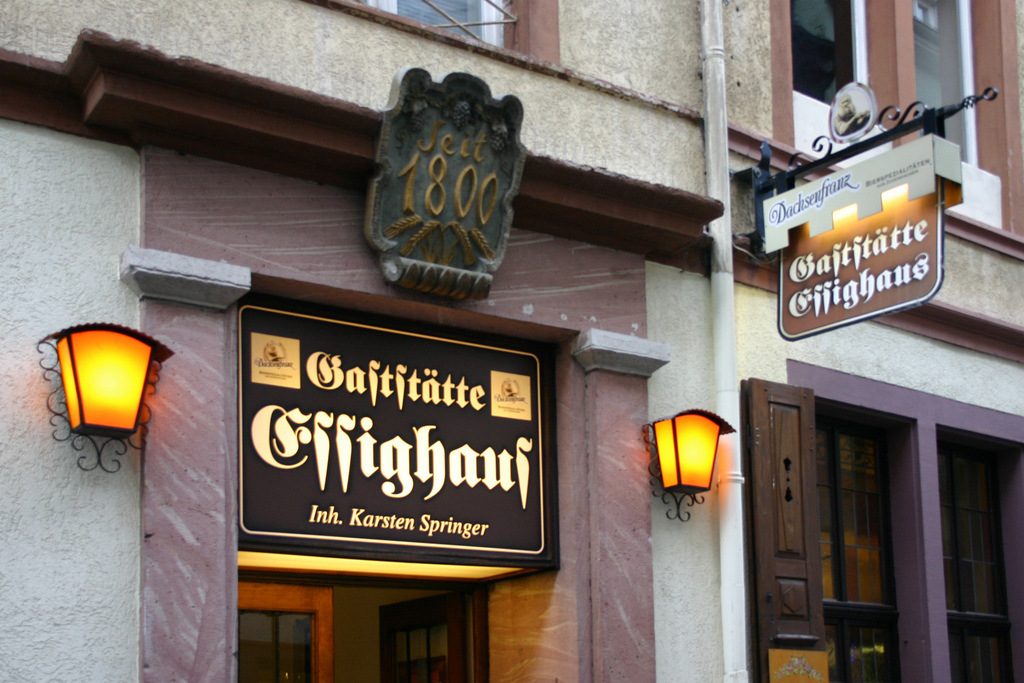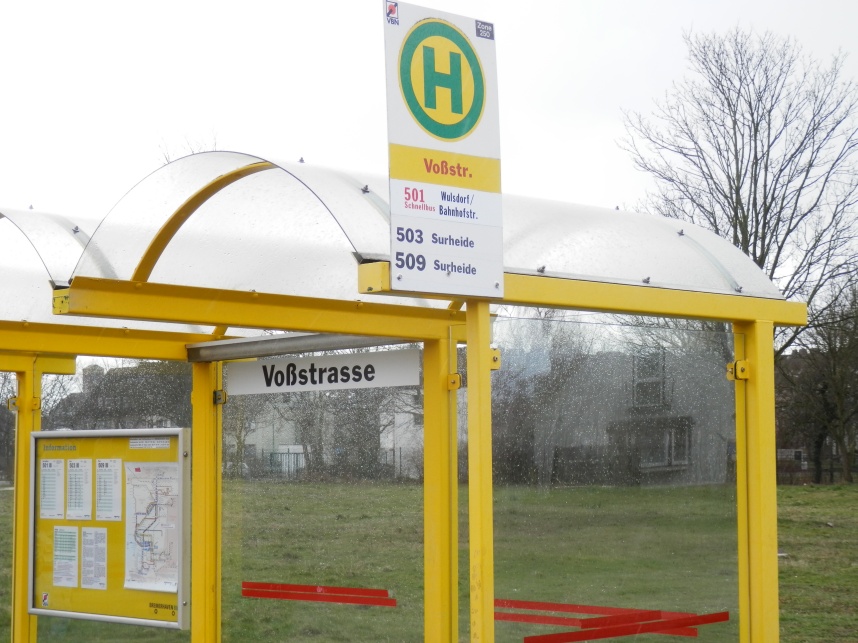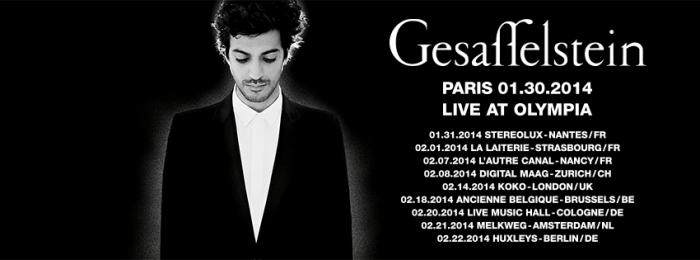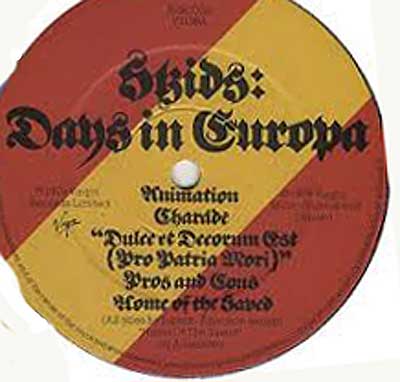
Neue Rechtschreibung?
Mir sieh diese Unsaubere Kantenführung einzig als das Ergebnis eines Autotracings aus.
Das war ja auch mein erster Gedanke, aber wenn man schon einen Billigklon einer bestehenden Schrift macht, dann verfertigt man doch normalerweise sicher keinen Auto-Tracing-Vector anhand eines Ausdrucks, sondern beschafft sich doch wohl eher die Originalschrift und zupft ein bißchen an den Ankerpunkten, oder?
Nachtrag zu der Norm-/Standard-/Empfehlungs-Diskussion: Kollege Mach hatte das auch schon früher mal in seinem Forum erklärt:
Die Untauglichkeit der PUA-Codes zum universellen Textsatz zeigt sich dann auch gleich. So erscheint das runde r als PUA-Zeichen bei mir im Browser:    ;-)
Nein, denn nicht selten sind solche Billig-Clones ja ohne Wissen über die Existenz oder gar dem Namen einer guten kommerziellen Schrift entstanden, sondern eben anhand einer irgendwo gefundenen Drucksache entstanden.
Hoppla! da hatte ich wohl meinen Test-Platzhalter vergessen, den ich in neue Schriften immer einbaue, um so bei meinen eigenen Tests sofort zu erkennen, dass hier nicht ein möglicherweise zu ähnliches Zeichen aus einem anderen Font per Fallback rein gekommen ist, sondernm der Fehler noch in meiner Schrift liegt.
Normalerweise haue ich das hinterher auch komplett raus, oder baude das normale .notdef-Kästchen ein.
Gibt’s dafür nicht auch schöne Ligaturen?
Eine Antiqua mit ſſ-Ligatur hat mit an Sicherheit angrenzender Wahrscheinlichkeit auch eine ff-Ligatur.
Zumindest hätte ich da sehr den Preis gedrückt - allerdings, ob ich es hätte hängen lassen?
Aber ich glaube, machdem man die Schriftgröße fest gelegt hatte, war fürs runde s kein Platz mehr da, dann nimmt man das schmale.
Oh jeh, nicht dass er das heraus gehängte Schild mit dem runden s auch noch als fehlerhaft ansieht, und es nur nicht durch ein "richtiges" ersetzt hat, weil grad kein Geld dafür bereit stand...
Immerhin: Wenn er den Unterschied nicht kennt, macht er bei »Gaststätte Essighaus« signifikant weniger Fehler mit der ſ-Beschränkung, als er mit einer s-Beschränkung machen würde. :-?
Wenn er kein rundes s mag, soll er's halt "Zum Essighause" nennen ;-)
Das ist ja nicht nur das falsche s, sondern dieses ist auch noch um 180° gedreht. Und das D sieht eigentlich auch eher ein bißchen wie ein N aus.
meine Theorie: dort fehlt ein Leerzeichen und das Tattoo ist noch nicht fertig.
»Deutsch and stupid«
Nein, nein, nein! Da tust du dem Menschen sicher unrecht. Tatsächlich ist der einfach nur sehr kosmopolitisch und will sich eben nicht auf seinen ethnischen Hintergrund beschränken lassen. Er sagt: Ich bin deutsch und …
Gerade durch das bewusste Offenlassen lässt er sich grenzenlos auf die ganze Welt ein und hält dem Betrachter, der ihn in eine Schublade stecken will, gleichzeitig einen Spiegel vor: Ich bin ein Individuum. Ich lasse mich nicht durch willkürliche Grenzen einengen. Du bist der Beschränkte.
Der das geklebt hat, hat einfach die neue Rechtschreibung nicht komplett verstanden, oder war nur verwirrt:
"Da war doch was mit ß und ss und den langen und kurzen Vokalen? OK, wenn ich Voß mit kurzem o ja mit ß schreiben soll, wird ss bei Straße mit langem a wohl richtig sein - hmm?"